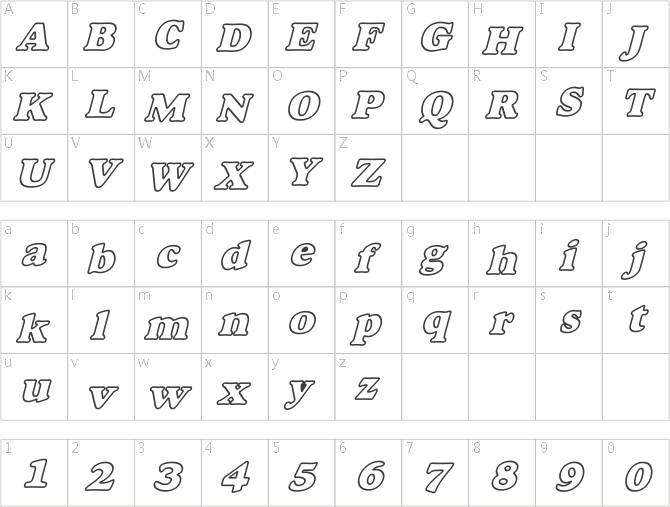
字体名称: Alexuss
Alexuss-Heavy-Hollow-W_BI-Bold-I
Alexuss-Heavy-Hollow-W_BI-Bold-I字体字库是一款让人赏心悦目、百看不厌的英文字体,适合各类广告和产品包装设计应用,字体大小0.19MB,格式为ttf字体,上传用户是afig,作者/版权方为未知